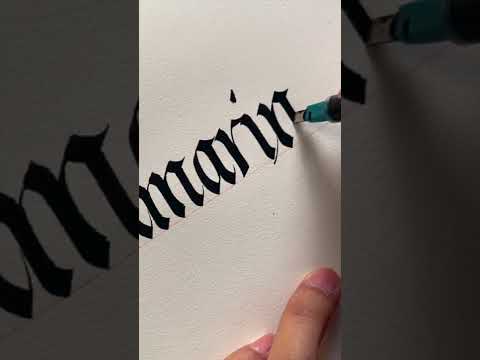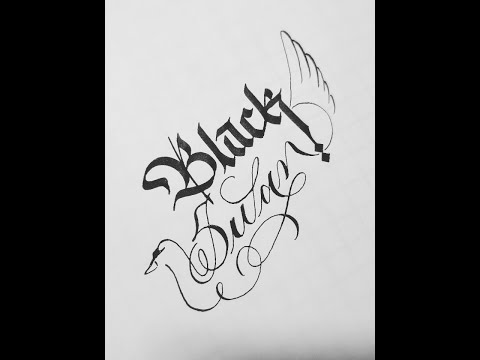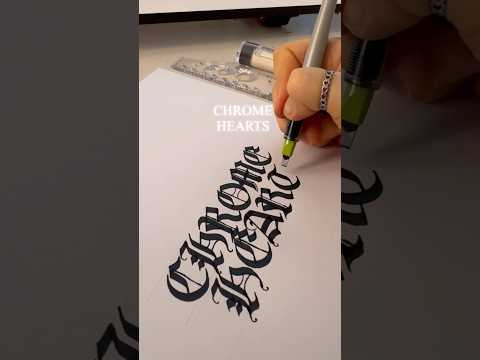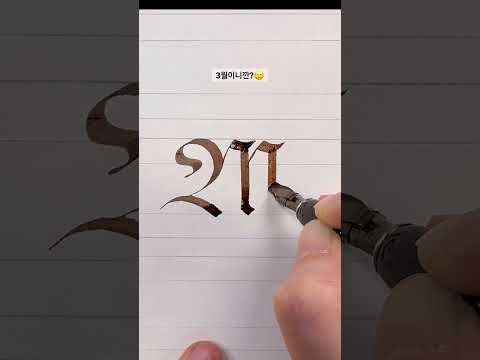
- 눈에 띄는 개성 넘치는 디자인 폰트! ✨
- 다양한 디자인 작업에 활용도 200%! 🎨
캘리그라피고딕체, 왜 핫할까? 🔥
캘리그라피고딕체, 이름부터 뭔가 예술적인 느낌이 뿜뿜하지 않나요? 🤩 흔한 고딕체는 너무 딱딱하고 재미없는데, 캘리그라피 느낌이 더해져서 훨씬 부드럽고 개성 넘치는 디자인을 완성할 수 있다는 사실! 🙌 마치 손으로 직접 쓴 듯한 자연스러움이 느껴져서, 디자인에 감성을 한 스푼 더해주는 느낌이에요. 😍
특히 요즘처럼 개성이 중요한 시대에, 뻔한 폰트로는 살아남을 수 없잖아요? 😭 캘리그라피고딕체는 흔하지 않으면서도 가독성이 좋아서, 어떤 디자인에도 찰떡같이 어울린답니다. 👍 로고, 배너, 웹 디자인, 영상 편집 등 활용도가 무궁무진하다는 거! 💯
게다가 캘리그라피고딕체는 다양한 굵기와 스타일을 제공해서, 디자인 컨셉에 맞춰 자유롭게 선택할 수 있다는 장점이 있어요. 😎 얇은 폰트로 세련된 느낌을 연출하거나, 굵은 폰트로 강렬한 인상을 남길 수도 있죠. 😜 이쯤 되면 만능 폰트라고 불러도 손색없겠죠? 👑``
폰트, 그냥 예쁘기만 한 게 다가 아니라는 사실! 🤔 폰트의 특징을 제대로 파악하고 사용해야 디자인의 완성도를 높일 수 있어요. 캘리그라피고딕체를 다른 폰트와 비교해볼까요? 🧐
폰트 종류 | 특징 | 장점 | 단점 | 활용 분야 |
---|---|---|---|---|
캘리그라피고딕체 | 캘리그라피의 멋과 고딕의 안정감이 조화된 폰트. 부드러우면서도 개성 있는 디자인. | 독특하고 세련된 느낌, 높은 활용도, 다양한 스타일 제공 | 가격이 비쌀 수 있음, 호불호가 갈릴 수 있음 | 로고 디자인, 웹 디자인, 광고 디자인, 출판 디자인, 영상 디자인 |
일반 고딕체 | 깔끔하고 가독성이 좋은 폰트. 딱딱하고 사무적인 느낌. | 높은 가독성, 다양한 종류, 저렴한 가격 | 개성이 부족함, 디자인이 밋밋함 | 문서 작성, 웹 디자인, 인쇄물 디자인 |
명조체 | 부드럽고 우아한 느낌의 폰트. 전통적인 느낌. | 고급스럽고 여성스러운 느낌, 가독성이 좋음 | 딱딱하고 올드한 느낌, 활용도가 제한적 | 출판 디자인, 서적 디자인, 전통적인 디자인 |
손글씨 폰트 | 손으로 직접 쓴 듯한 자연스러운 느낌의 폰트. 개성 넘치는 디자인. | 독특하고 개성 있는 느낌, 친근하고 따뜻한 느낌 | 가독성이 떨어질 수 있음, 퀄리티가 낮은 폰트가 많음 | 개인적인 블로그, SNS, 이벤트 페이지 |
표에서 보시다시피, 캘리그라피고딕체는 독특함과 활용도 면에서 다른 폰트들보다 훨씬 뛰어나다는 것을 알 수 있어요. 😉 물론 가격이 조금 비쌀 수 있지만, 그만큼의 가치를 충분히 한다는 거! 👍
저는 주로 웹 디자인 작업을 하는데, 캘리그라피고딕체를 사용하고 나서 클라이언트들의 반응이 훨씬 좋아졌어요. 😍 폰트 하나 바꿨을 뿐인데, 디자인 퀄리티가 확 올라간 느낌! 👍 특히 젊은층을 타겟으로 하는 디자인에 캘리그라피고딕체를 활용하면, 훨씬 트렌디하고 세련된 느낌을 줄 수 있답니다. 😎
장점:
- 개성 넘치는 디자인
- 높은 활용도
- 세련된 느낌
- 가독성 좋음
단점:
캘리그라피고딕체, 이렇게 활용해봐! 꿀팁 대방출 🍯
캘리그라피고딕체, 어떻게 활용해야 더 예쁠까요? 🤔 저만의 꿀팁을 여러분께만 살짝 공개할게요! 😉
- 로고 디자인: 캘리그라피고딕체는 로고에 개성을 더하고 싶을 때 활용하면 좋아요. 폰트 자체의 독특한 디자인 덕분에, 로고가 훨씬 눈에 띄고 기억에 남을 거예요. 👍
- 웹 디자인: 웹사이트 제목이나 강조하고 싶은 부분에 캘리그라피고딕체를 사용하면, 방문자들의 시선을 사로잡을 수 있어요. 😍 특히 배너 광고나 이벤트 페이지에 활용하면 효과 만점! 💯
- SNS 콘텐츠: 인스타그램, 페이스북 등 SNS 콘텐츠에 캘리그라피고딕체를 활용하면, 훨씬 트렌디하고 감각적인 느낌을 줄 수 있어요. ✨ 썸네일 이미지나 텍스트 강조에 활용해보세요! 😜
- 영상 편집: 영상 자막이나 타이틀에 캘리그라피고딕체를 사용하면, 영상의 분위기를 더욱 풍성하게 만들어줄 수 있어요. 🙌 특히 감성적인 영상이나 개성 넘치는 영상에 잘 어울린답니다. 😎
- 프레젠테이션: 딱딱한 프레젠테이션 자료에 캘리그라피고딕체를 적절히 활용하면, 훨씬 부드럽고 친근한 인상을 줄 수 있어요. 😉 중요한 부분에 포인트를 주거나, 인용구를 강조할 때 활용해보세요! 🥰``
캘리그라피고딕체 후기를 통해 폰트의 중요성을 다시 한번 느끼셨기를 바랍니다! 디자인의 완성도를 높이는 것은 물론, 개성까지 더할 수 있는 캘리그라피고딕체의 매력에 푹 빠져보세요! 😍 캘리그라피 폰트와 예쁜 손글씨체를 활용해서 더욱 멋진 디자인을 만들어보세요. 🎨
캘리그라피 고딕체는 딱딱한 고딕체의 정직함에 캘리그라피의 자유로운 표현을 더한 서체입니다. 정형화된 틀 안에서 개성을 드러내기 때문에 가독성을 유지하면서도 독창적인 느낌을 줄 수 있습니다. 제목이나 강조하고 싶은 부분에 사용하면 시선을 사로잡는 효과가 있습니다.